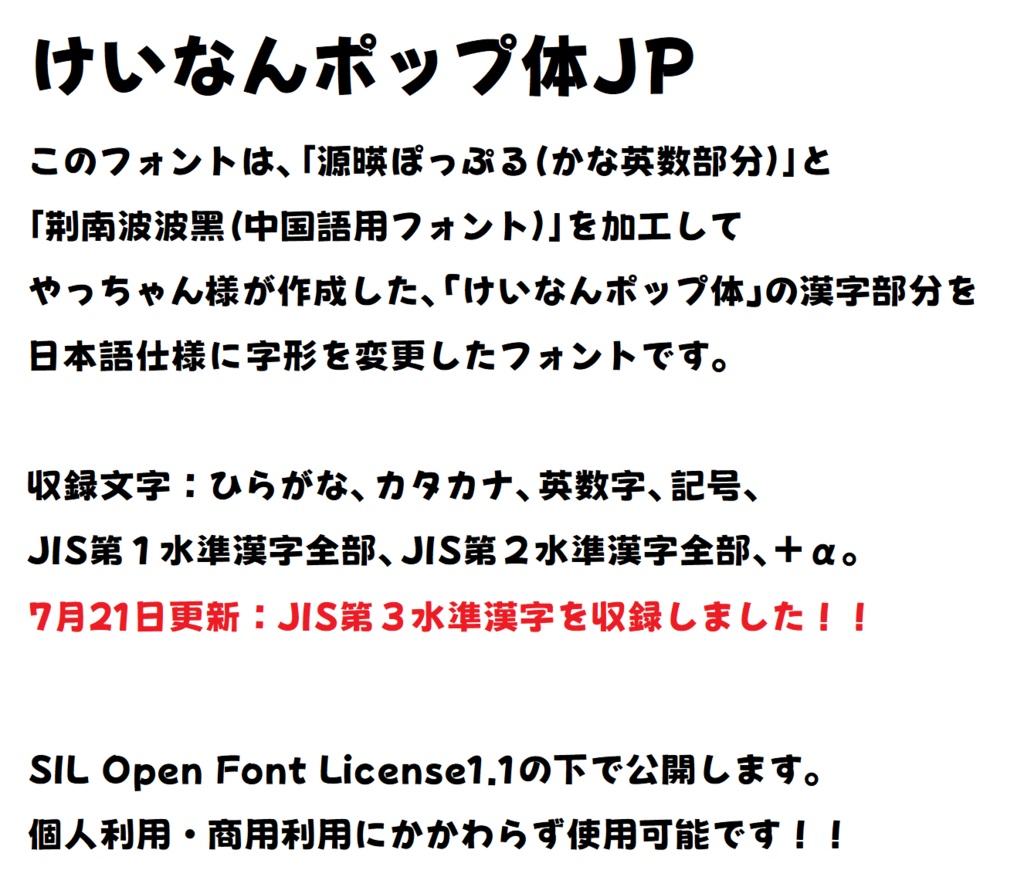
けいなんポップ体JP(10/31漢字の誤字を修正)
このフォントは「源暎ぽっぷる」と、中国語用フォント「荆南波波黑」を加工して、 やっちゃん様が作成した「けいなんポップ体」の漢字部分を JIS第1水準漢字を中心に日本語仕様に字形変更したり 足りない漢字を補ったりしたフォントです。 このフォントに関しては、SIL Open Font License1.1の下で公開します。 このフォントに関しては、以下のフォントを使用、加工しています。 関係者の皆様には深くお礼申し上げます。 ★けいなんポップ体(やっちゃん様) https://booth.pm/ja/items/6874288 ★源暎ぽっぷる(おたもん様) https://okoneya.jp/font/genei-pople.html ★荆南波波黑(荆南字庫(Kingnam Type Foundry)様、NightFurySL2001様) https://github.com/maoken-fonts/KNBobohei SIL Open Font Licenseとは? SILライセンス原文 http://scripts.sil.org/OFL ライセンス原文日本語サイト https://licenses.opensource.jp/OFL-1.1/OFL-1.1.html ライセンスざっくり解説(たぬき侍様) https://tanukifont.com/sil/ 収録文字:ひらがな、カタカナ、英数字、記号、 JIS第1水準漢字全部、JIS第2水準漢字全部、 JIS第3水準漢字全部、オマケの漢字(画像4枚目を参照)。 なお、「荆南波波黑」に収録済みだった簡体字などは 軽量化などの都合で削除していますので、ご了承ください。 また、縦書きについての保証は出来ませんのであしからず。 7月21日更新:JIS第3水準漢字全部を収録しました。(画像3枚目を参照) また、第1第2水準漢字でのさらなる字形修正を行いました。 7月30日更新:「極」「亟」「函」の字形を修正しました。 重ね重ね申し訳ございません。 8月7日追記:おまけの漢字に「𩸽(ほっけ)」も収録しています。 10月31日更新:「誚」「釀」が違う漢字になっていたため修正しました。